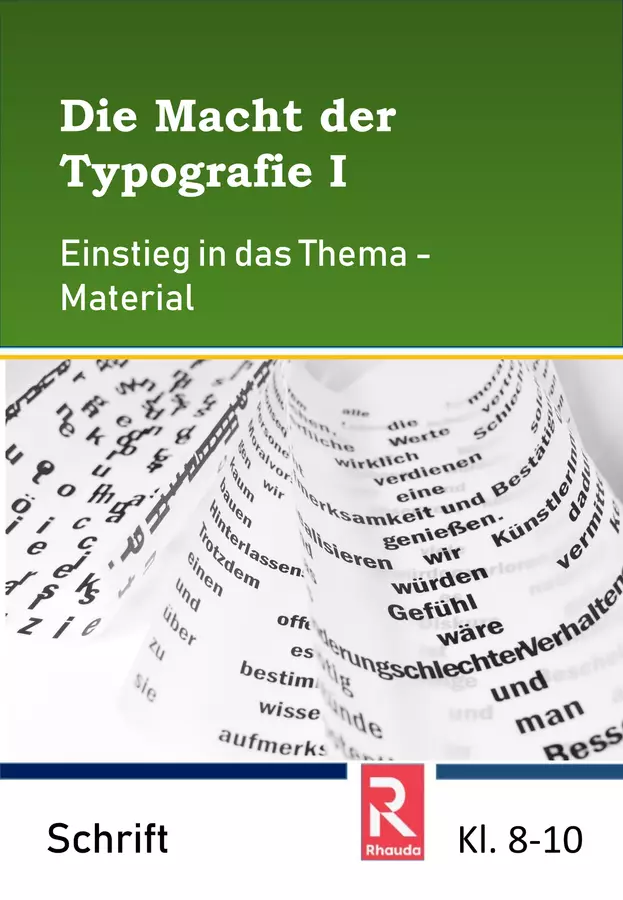
Tauche mit deinen Schüler*innen in die faszinierende Welt der Typografie ein! Dieses Material bietet dir eine spannende Doppelstunde, um die Macht der Schrift zu entdecken. Deine Schüler*innen lernen, wie Schriftarten wirken, welche Typografie-Regeln wichtig sind und wenden ihr neues Wissen direkt am Computer an.
• Eine interaktive Präsentation führt deine Schüler*innen spielerisch in das Thema ein. Sie sehen, wie ein und derselbe Satz in verschiedenen Schriftarten eine völlig andere Wirkung entfaltet.
• Spannende Arbeitsblätter laden zum Entdecken ein: Deine Schüler*innen analysieren die Beziehung zwischen Schrift und Inhalt bei Einzelwörtern und ordnen Schrifttypen passende Eigenschaften zu.
• Sie lernen, welche Schriftarten für unterschiedliche Anlässe und Zielgruppen am besten geeignet sind.
• Zwei kurze Videolinks mit QR-Codes bieten zusätzliche Impulse. Hier erklärt ein Profi die Grundregeln der Typografie und gibt wertvolle Tipps zur Schriftwahl.
• Eine kreative praktische Aufgabe am Computer fordert deine Schüler*innen heraus: Sie gestalten eine Einladung für ein selbst gewähltes Event und wenden dabei ihr frisch erworbenes Typografie-Wissen an.
• Wirkung von Schriftarten erkennen: Deine Schüler*innen verstehen, wie verschiedene Schriftarten Emotionen und Botschaften beeinflussen.
• Grundlagen der Typografie beherrschen: Sie lernen wichtige Regeln für eine gelungene Schriftgestaltung kennen.
• Schriftarten gezielt auswählen: Deine Schüler*innen können passende Schriftarten für unterschiedliche Kontexte und Zielgruppen identifizieren.
• Praktische Anwendung am Computer: Sie setzen ihr Wissen direkt um und gestalten eigene Texte typografisch ansprechend.
• Kritisches Denken entwickeln: Sie reflektieren über die Wirkung von Schrift in Alltagssituationen und Medien.
Die Macht der Typografie I